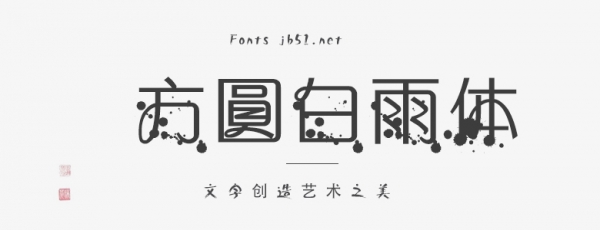
方圓白雨體是一款非常不錯(cuò)的藝術(shù)字體,工整簡(jiǎn)潔,具有強(qiáng)烈的視覺(jué)沖擊力,適應(yīng)于報(bào)紙和雜志和書(shū)籍中常用字體, 海報(bào)、個(gè)性促進(jìn)品牌標(biāo)志設(shè)計(jì)、字體設(shè)計(jì)、等環(huán)境使用,歡迎喜歡的朋友前來(lái)字體家下載使用.